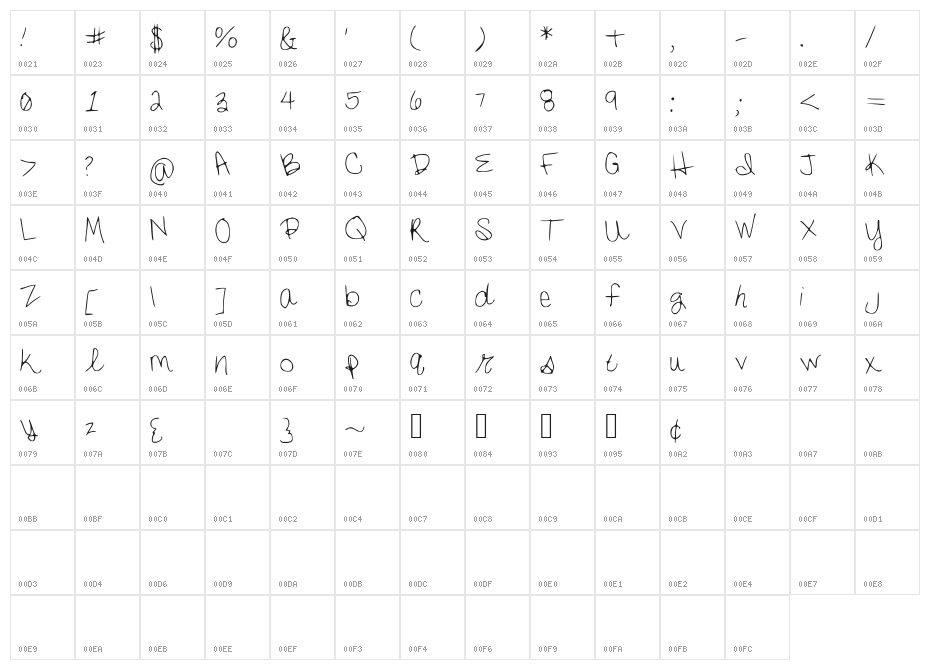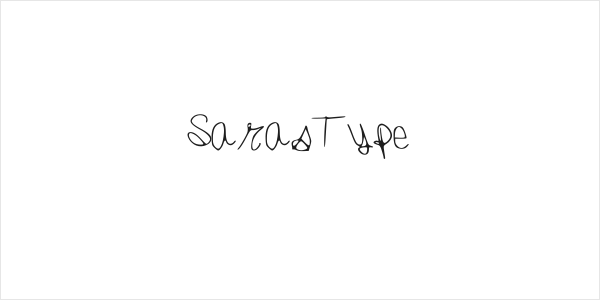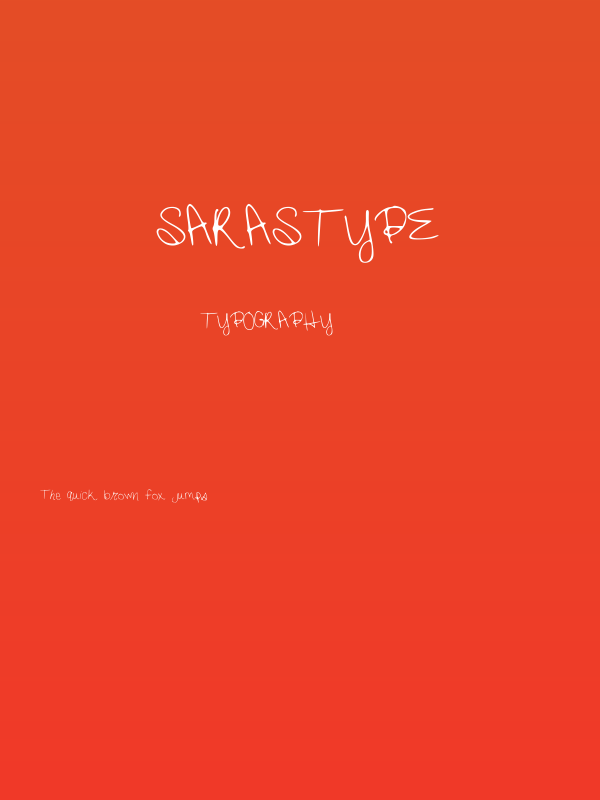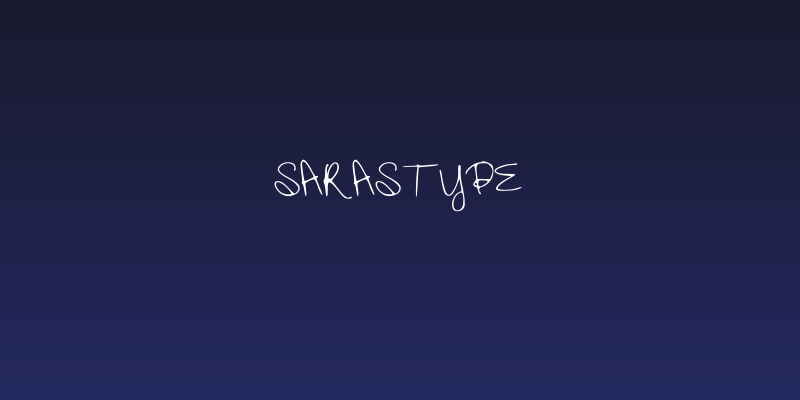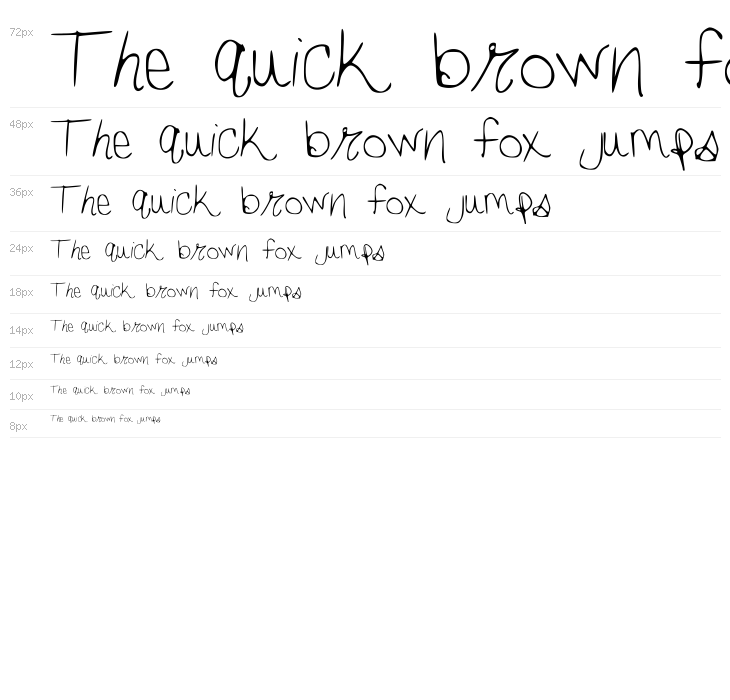
SarasType Font
| Caso d'uso | Headlines, Logos, Creative projects |
| Progetti proposti | Ideal for greeting cards, invitations, children's books, and creative branding projects. |